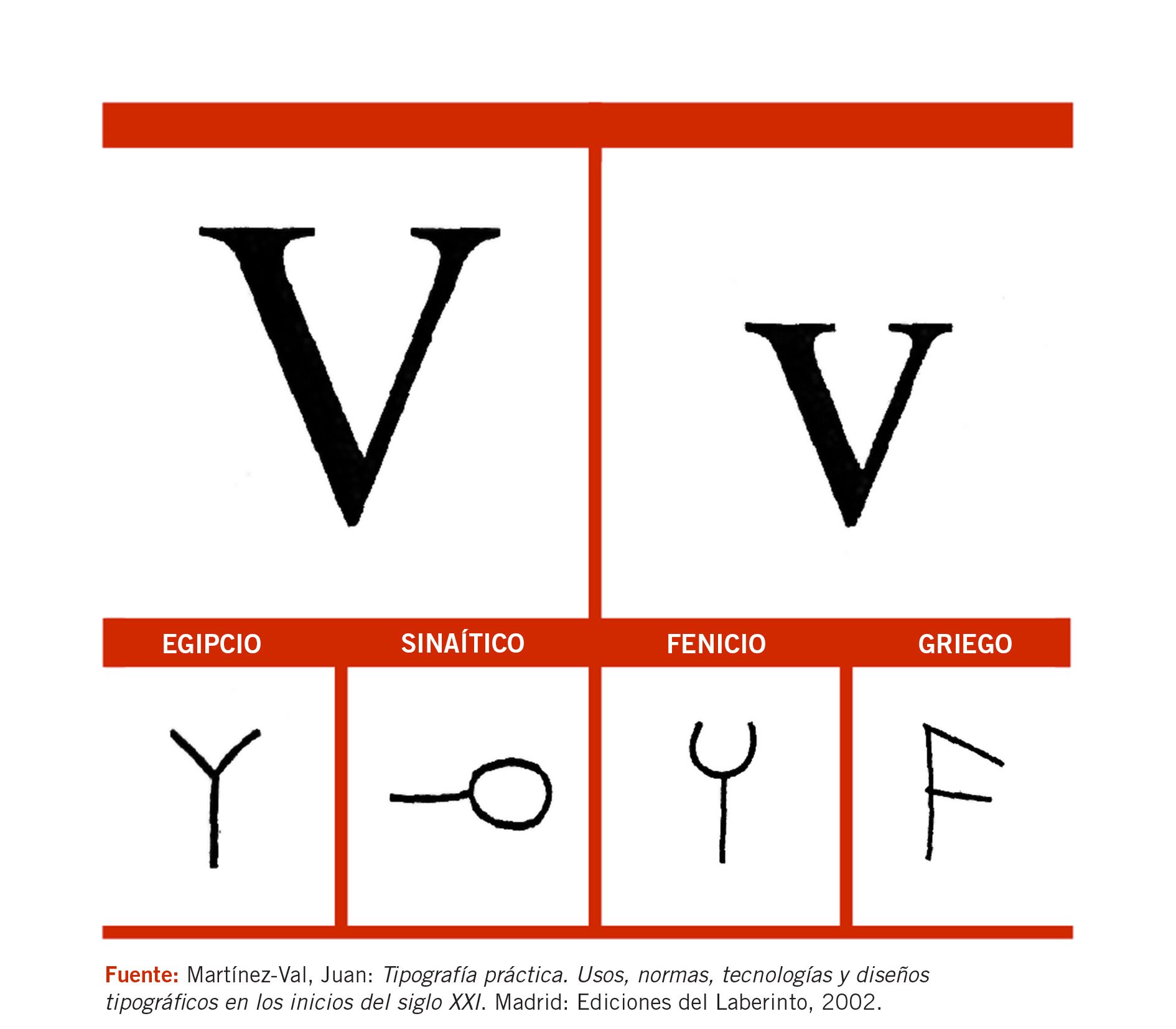
Griego arcaico 800 aC • Griego oriental 400 aC • Griego occidental 400 aC
Etrusco 800 aC • Latín clásico 200 aC • Romano 100 aC
Vigésima quinta letra del abecedario español, y vigésima segunda del orden latino internacional. Su nombre es uve, ve, ve baja o ve corta
La historia de la letra v se corresponde con la de la letra u.
Los romanos no tuvieron sonido “V”. En cuanto a la minúscula ha existido en versiones caligráficas muy redondeadas, similares a la “u”, pero la imprenta recogió en mayor medida la agudeza de la versal.
Tipografía Vendôme, F. Ganeau y R. Excoffon. 1952
Alfabeto Nude, creado por A&A Beeke y fotografiado por G. Kooiman, 1970.
| Lubalin graph book |
Officina Book |
| Alfabeto ornamental diseñado por J. L. Pouchée (1820). |